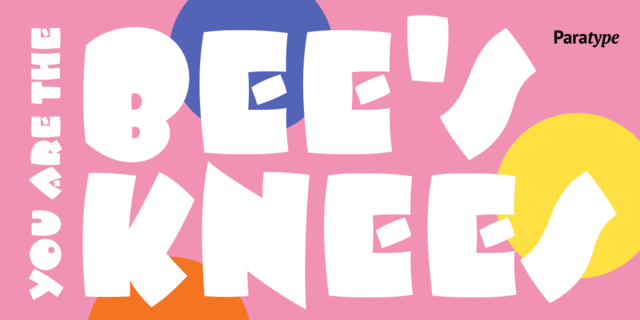
Шрифт разработан для фирмы International Typeface Corporation в 1990 (дизайнер Дэвид Фэри). Очень жирные прописные без засечек кажутся написанными широкой кистью. Предназначен для применения в рекламе и акциденции. Кириллическая версия разработана в фирме ПараТайп (ПараГраф) в 1994 (дизайнеры Татьяна Лыскова, Эльвира Слыш).
яркий, сильный, черный, тесный, мощный, громкий, характерный, динамичный, выразительный, забавный, ироничный, здоровый, праздный, гуляющий, балованный, щедрый, тусовочный, прикольный, живой, неформальный, броский, веселый, задорный, радостный, игривый, подвижный, оригинальный, заметный, детский, карикатурный, мультяшный, остроумный, счастливый, праздничный, творческий, тяжелый, смешной, непослушный, летний, жаркий, артистичный, озорной, непоседливый, наивный, сумасбродный, прожорливый, активный, южный, кричащий, вернакулярный, дружелюбный, добродушный, добрый, приветливый, спелый, вкусный, милый, домашний, пышный, доброжелательный, гладкий, семейный, улыбчивый, аппетитный, сладкий
игра, приключения, фаст фуд, лавка, игрушка, развлечения, вечеринка, реклама, зоопарк, кафе, детская книжка, юмор, анимация, завтрак, еда, закуска, раскраска, отдых, цирк, мультфильм, каникулы, пицца, животные, сувенир, аттракцион, аквадискотека, графика, иллюстрация, булочка, десерт, сладости, кондитерская, мягкая игрушка, семья, краски, краска, школа, лагерь, детское питание, клоун, зоомагазин, детский сад, утренник, сок, торт, шоу, телевидение, мороженное, подгузник, сыр, дом, утро Стилистика: